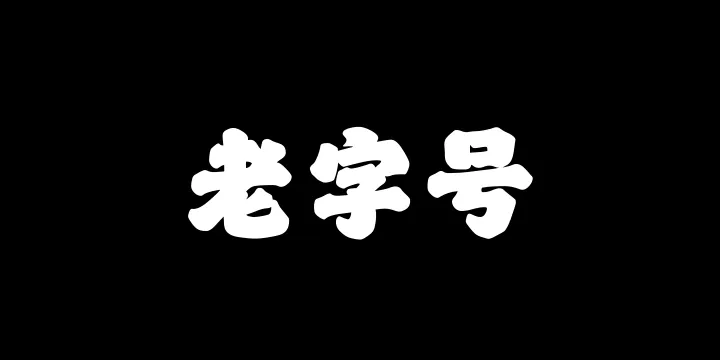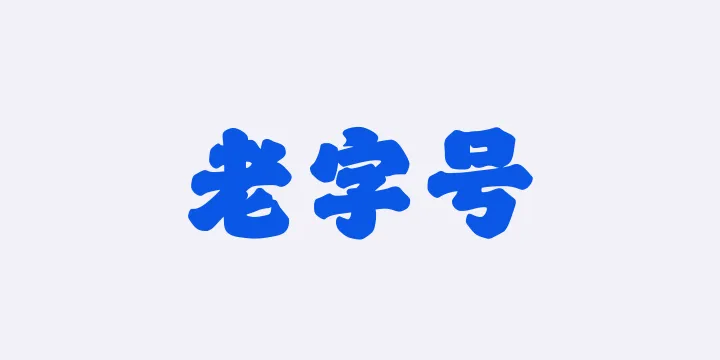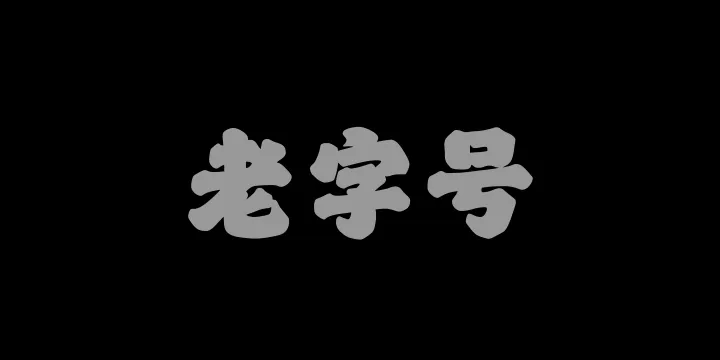
山海老字号W By 山海字库 商用字体
字体全名: 山海老字号W
字体简介: 山海老字号,包含简繁汉字9169个,是一款擘窠大字榜书字体。该字体雄健有力,非常醒目!融入楷书特点,有力、宽厚、方正,如同巍峨的大山,充满了稳重感和设计感。古朴浑厚,笔画与字形间透露着榜书的古雅和刚劲的特点,在浑厚的同时而又极富张力,桀骜不驯的特性,霸气外露。它的笔画充满力量感,组合搭配极富强烈的节奏感。在粗细的纵横间,拥有非常规的张力特性。